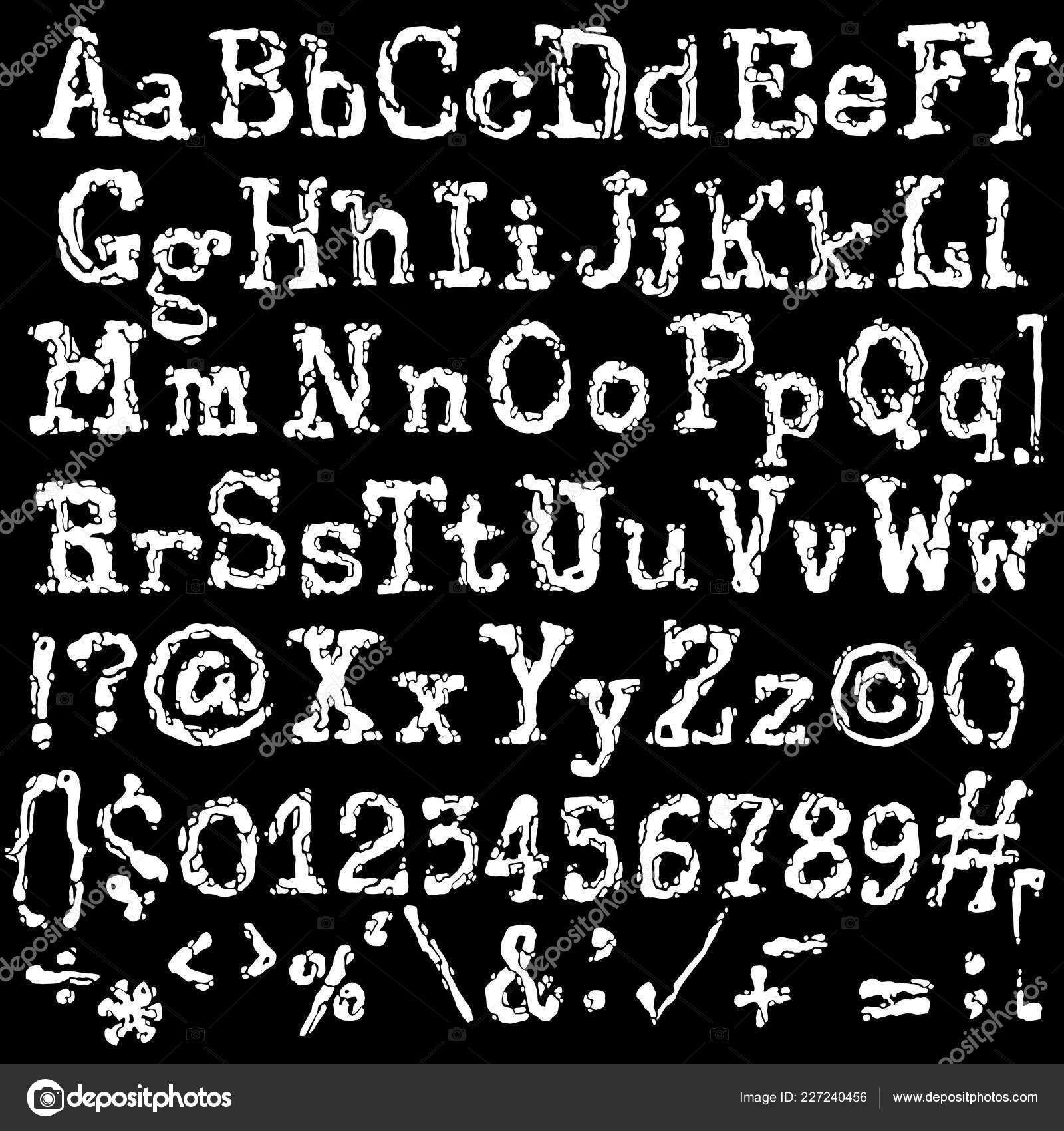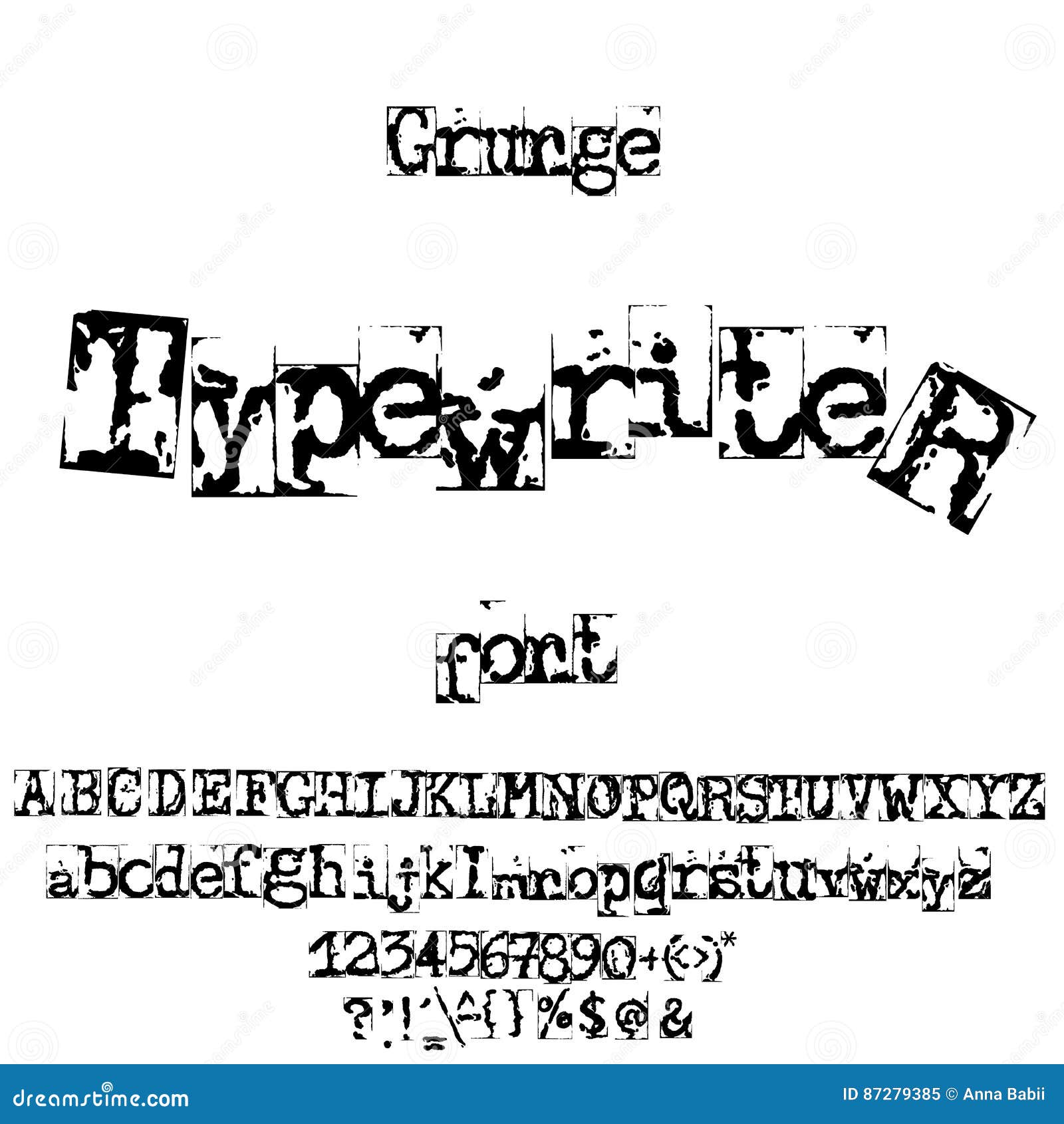
Печатная машинка с таким циферблатом определенно была высшего качества. Скачать другую пишущую машинку.
Итак, мы завершаем нашу десятку лучших шрифтов для американских пишущих машинок, предлагая что-то для всех.